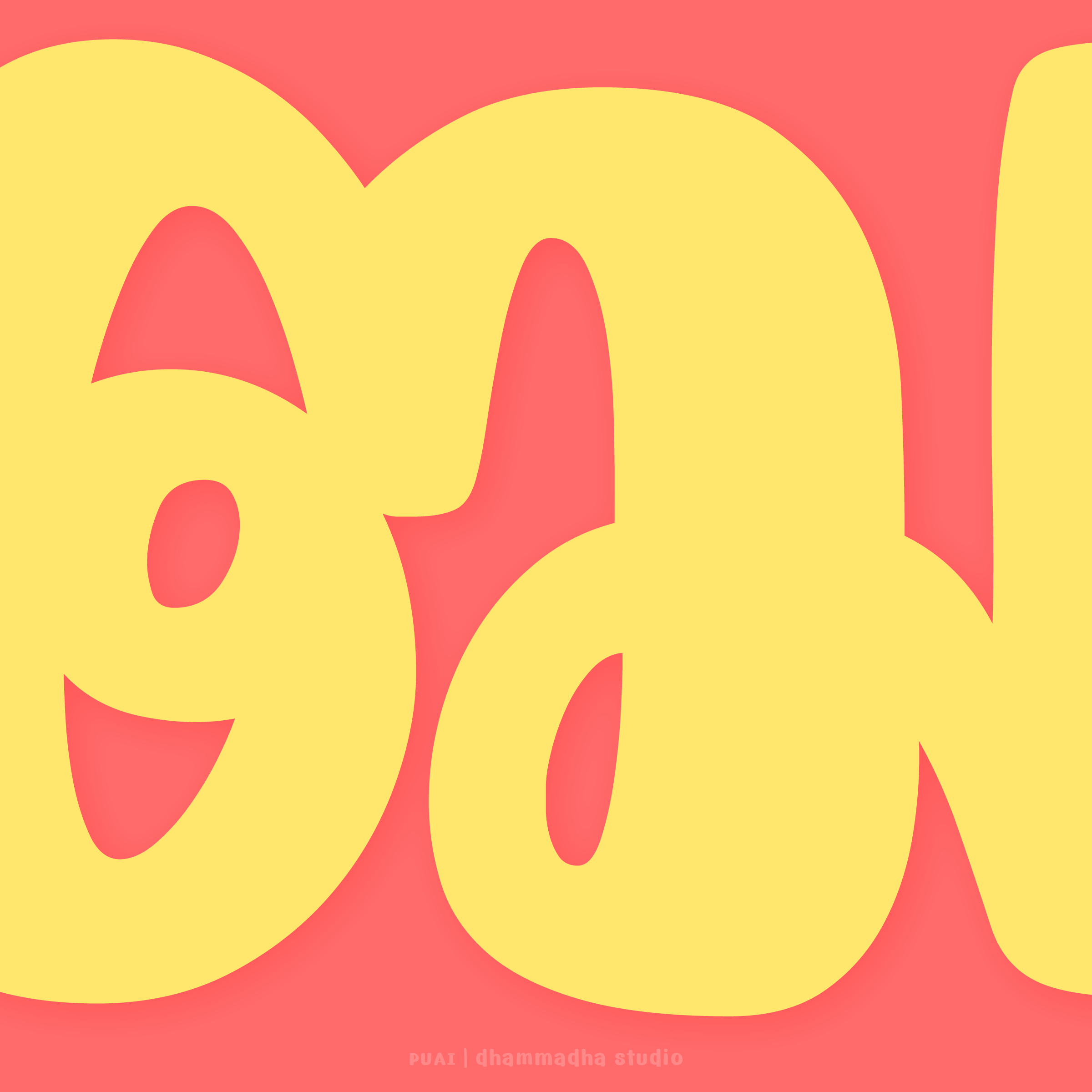
ป๋วย | PUAI
ลายมือแอดป๋วยจากเพจ RUNNING TORTOISE
เจ้าของความคิดฟอนต์ DONGTAO ที่เคยปล่อยออกไปแล้ว
PREVIEW คร่าว ๆ ว่าบุคลิกประมาณนี้ฮะ
ชื่อฟอนต์ : ป๋วย | PUAI
ป๋วย | PUAI
ฟอนต์ลายมือ จากแอดมินอ้วน เพจ RUNNING TORTOISE
เจ้าของไอเดียฟอนต์สุดจ๊าบ ดองเต่า | DONGTAO
ใช้งานง่าย เป็นธรรมชาติ
จัดเต็มด้วย Ligature และ Alternative Glyph มากมายเช่นเคย
ชุดฟอนต์ "ป๋วย"
ประกอบด้วยฟอนต์ 3 น้ำหนัก 6 ฟอนต์
REGULAR / BOLD / BLACK + ITALIC
ออกแบบโดย : Montonn Thanaroj